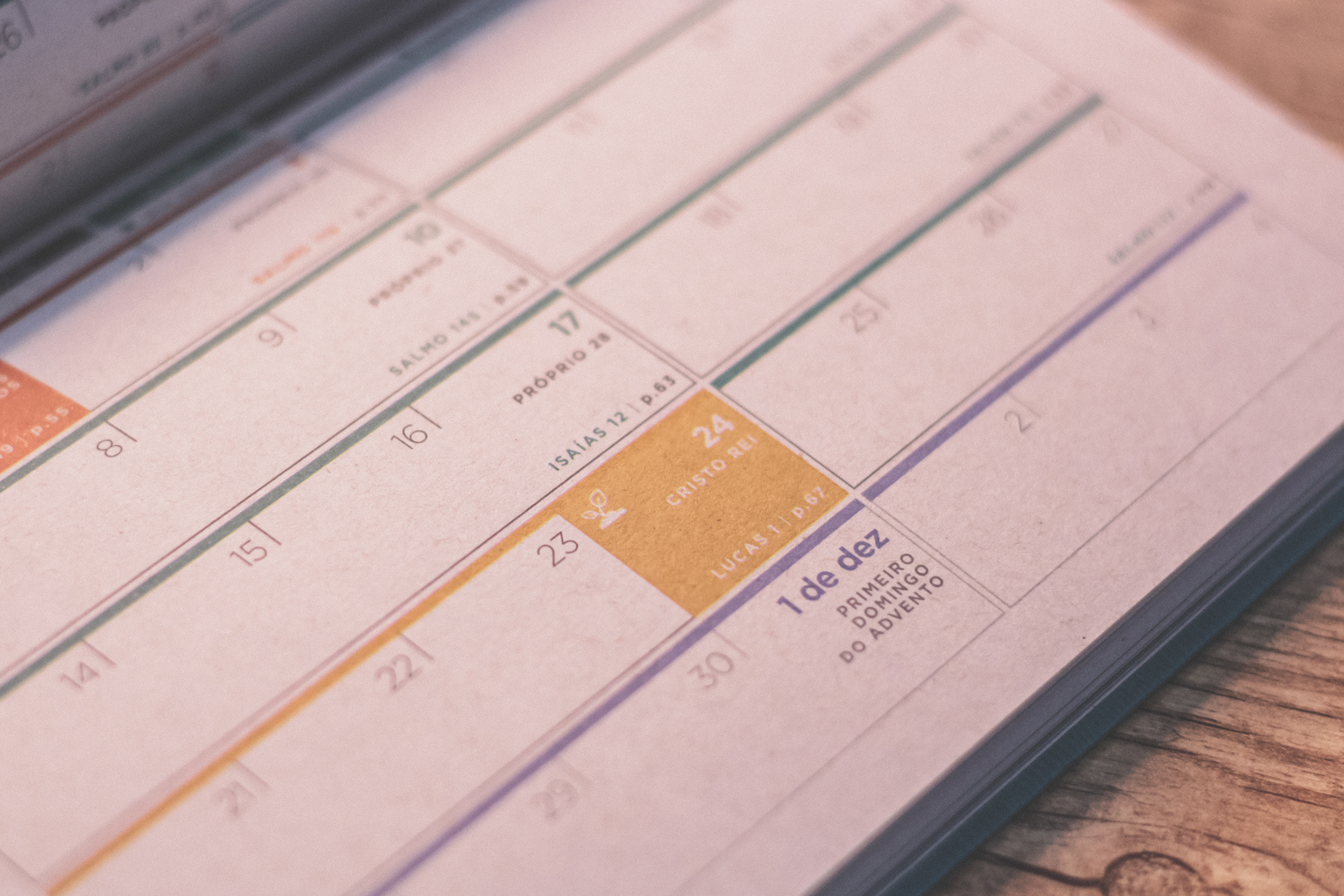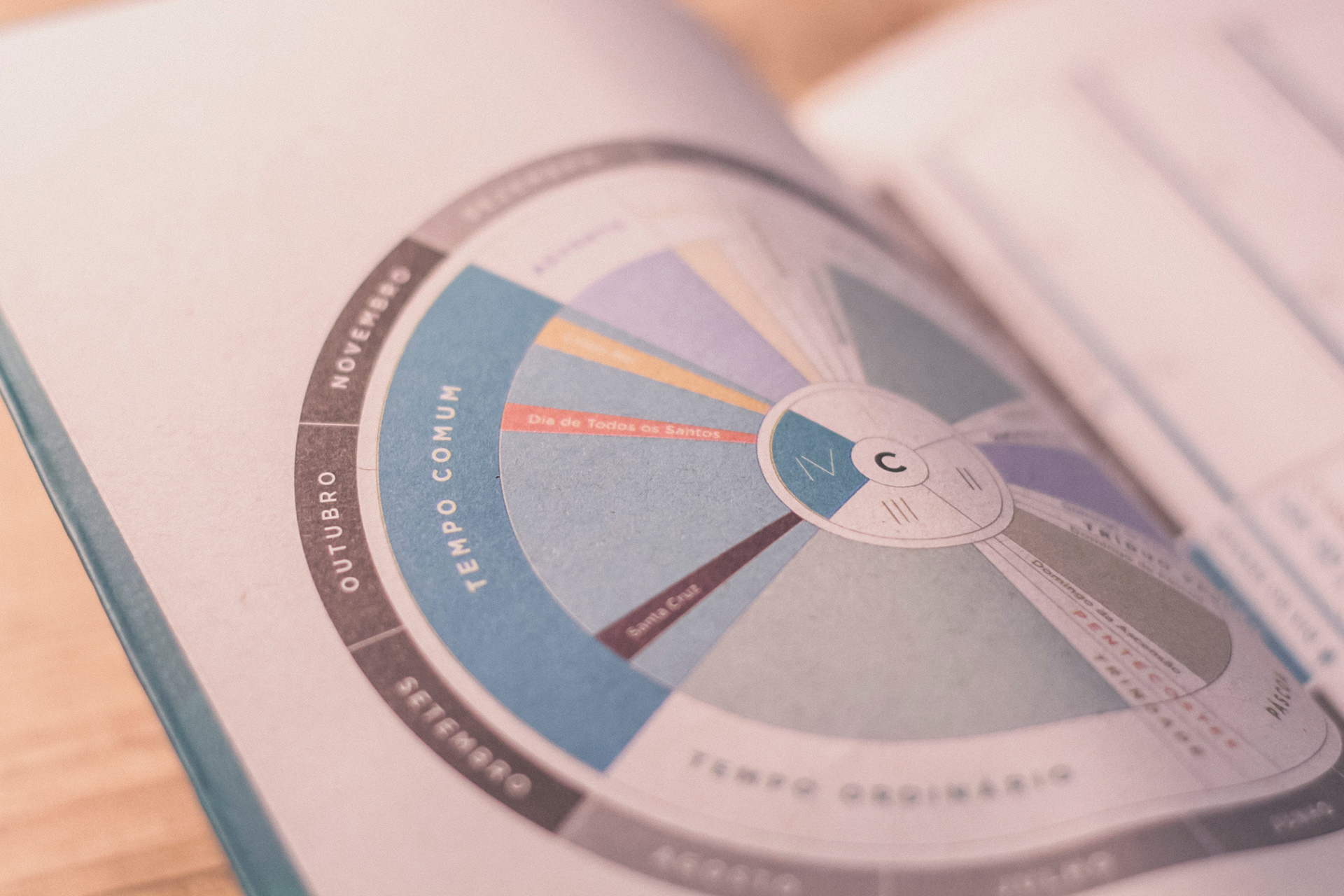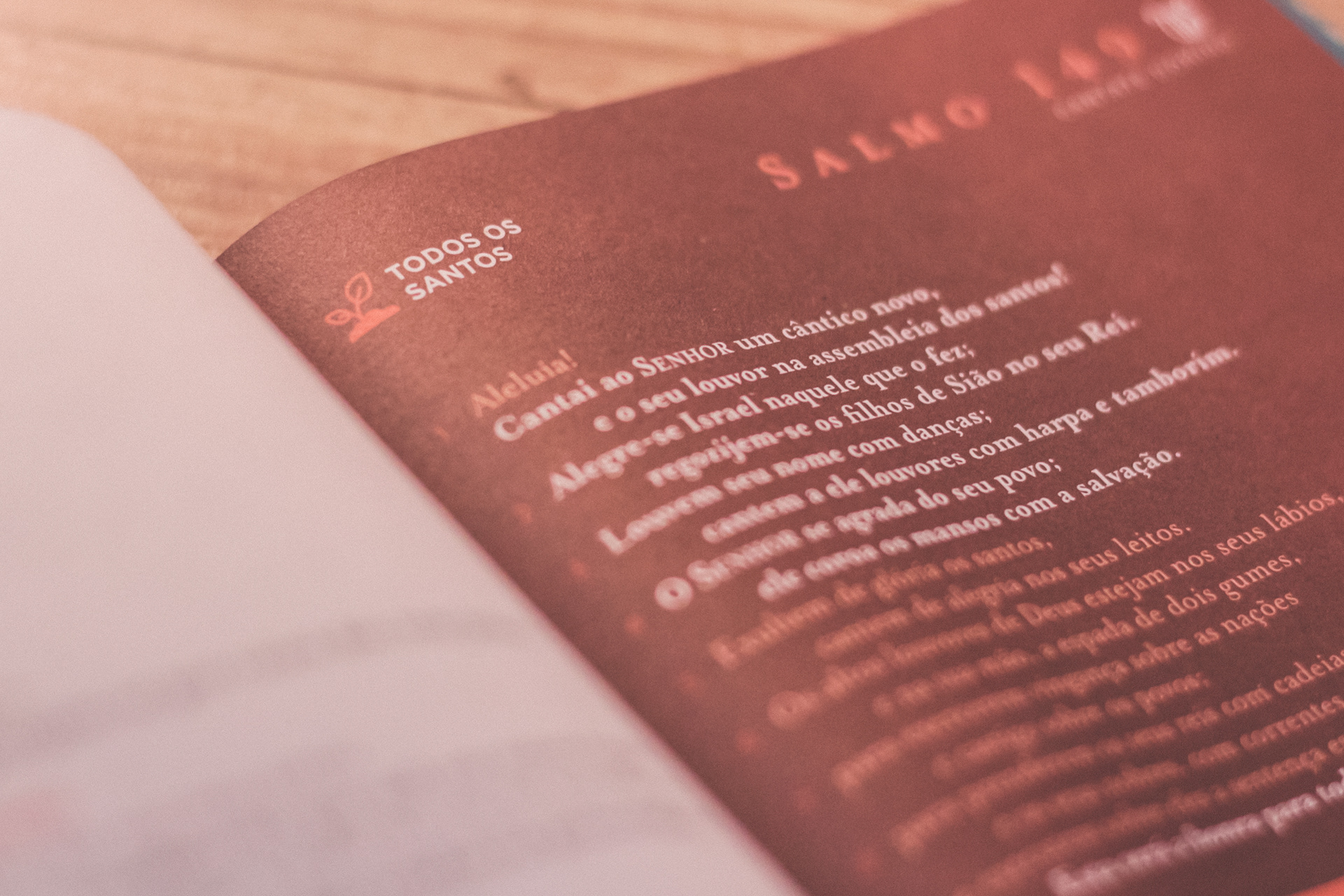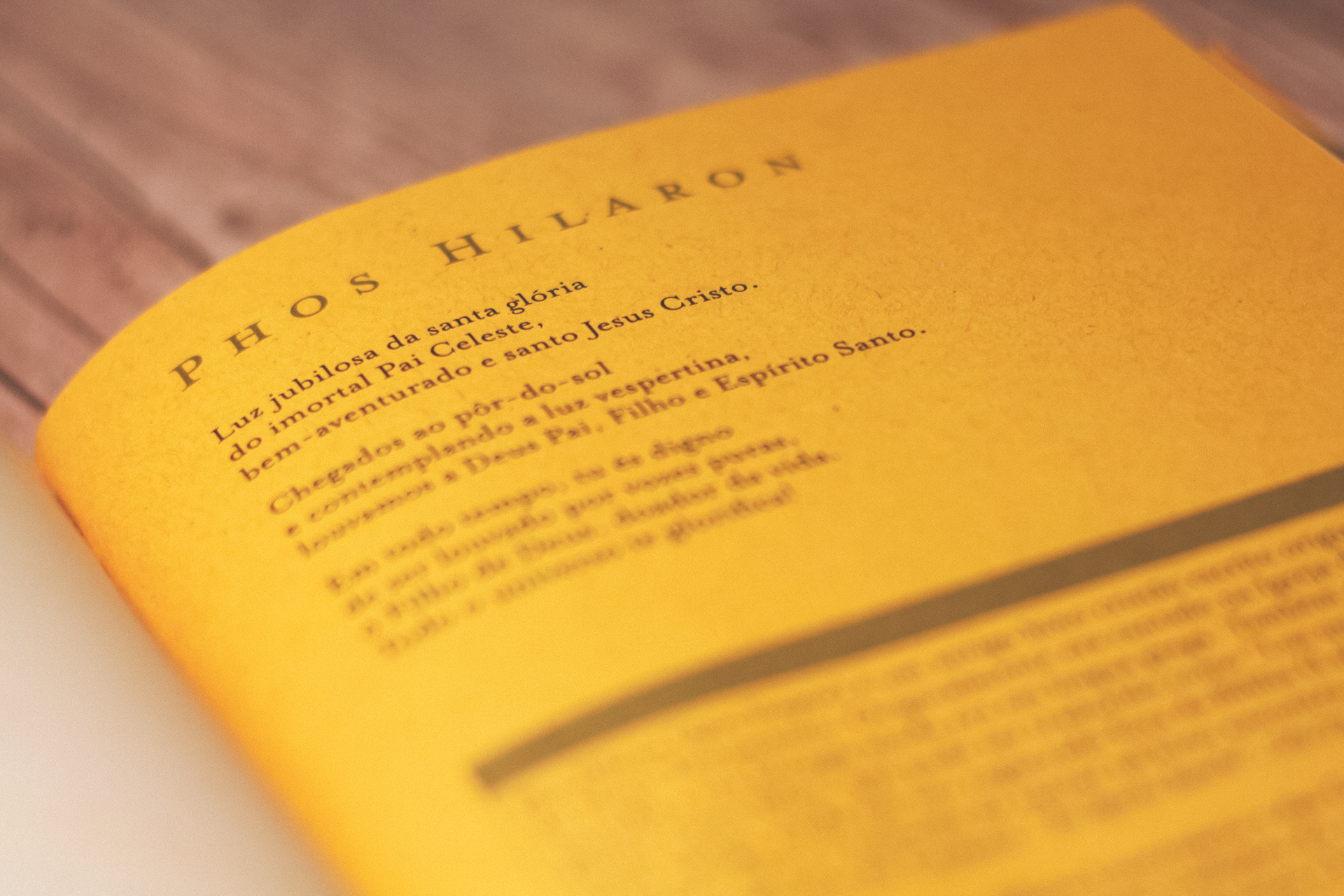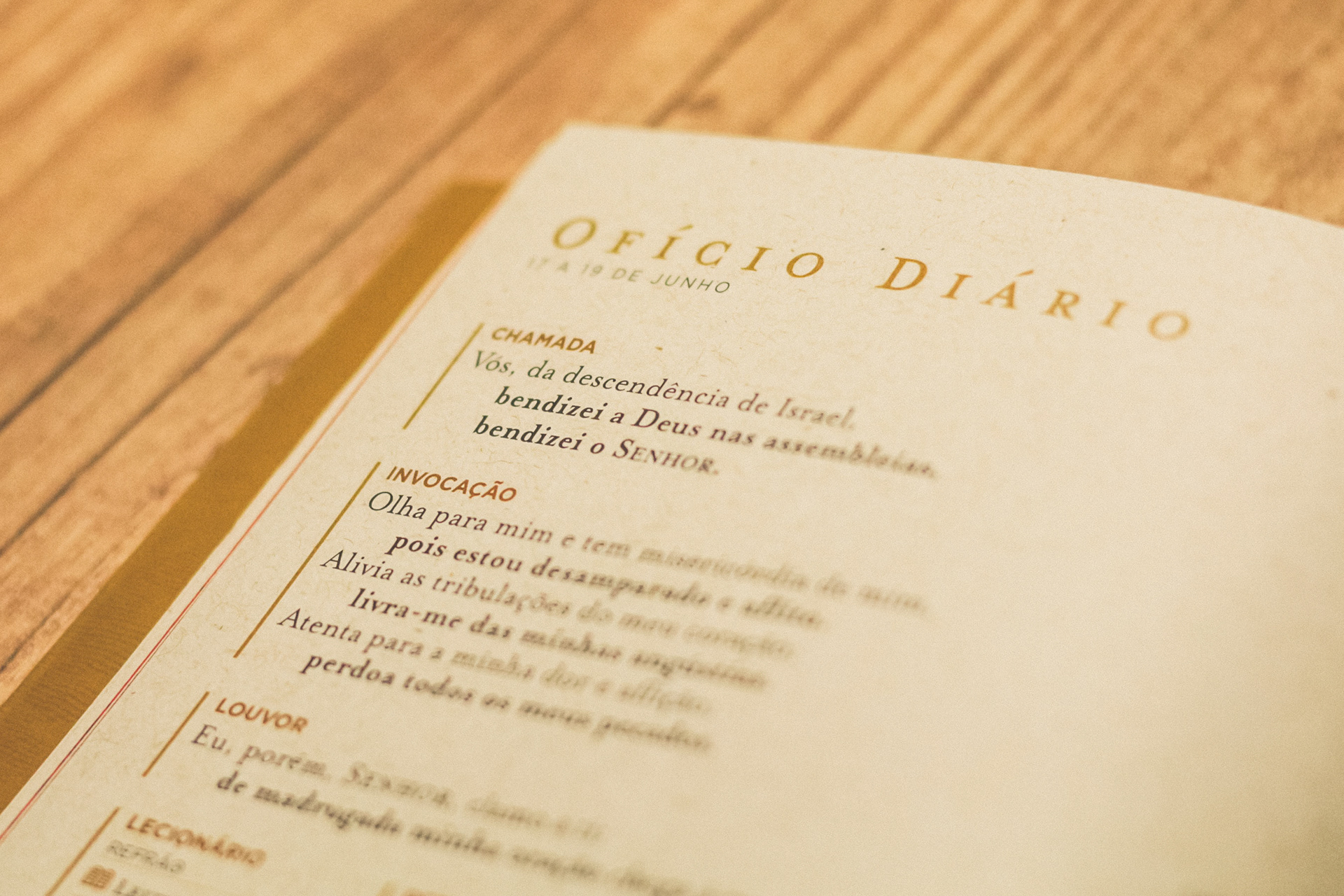
Lecionário
Redesign de Identidade Visual, Criação de Projeto Gráfico e Diagramação dos produtos editoriais do projeto Lecionário que resgata a tradição litúrgica cristã como ferramenta devocional individual e coletiva
A expressão “Ancient-Future”, cunhada por Robert E. Webber para descrever o resgate da tradição antiga como uma resposta para o futuro da igreja, reflete bem o espírito desde projeto, de buscar alternativas para apresentar uma riqueza inestimável da tradição cristã numa linguagem e estética contemporâneas. O grande desafio tem sido traduzir a serenidade litúrgica dos primeiros séculos da igreja para o agitado coração de amores desordenados dos nossos dias.
Assim, após 2 anos de muita experimentação, consolidando algumas coisas e renovando outras, apresentamos o nossa maior renovação gráfico-visual. Aderimos à Litúrgica Dingbats, projetada pelo querido Kaiky Fernandez, como iconografia oficial do @lecionario. E inspirados nela, redesenhamos a nossa identidade visual para trazer ainda mais leveza e frescor numa comunicação muito simples, mas que busca aprofundar o dialogo com a sociedade da informação.